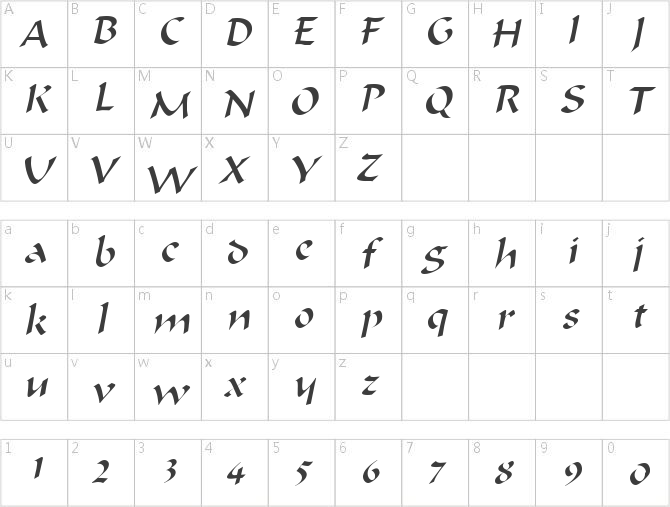
Marlin-Thin-Italic 詳情頁(yè)
Marlin-Thin-Italic字體字庫(kù)是一款讓人賞心悅目、百看不厭的英文字體,適合各類廣告和產(chǎn)品包裝設(shè)計(jì)應(yīng)用,字體大小0.06MB,格式為ttf字體,上傳用戶是W^xzj,作者/版權(quán)方為未知